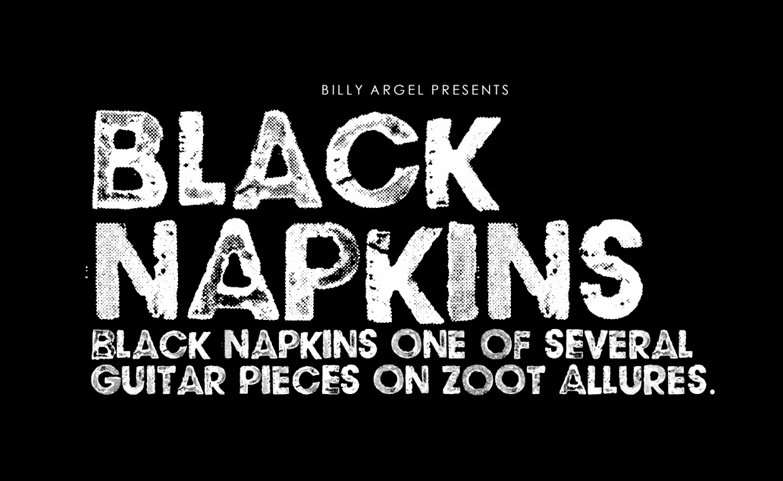
BLACK NAPKINS Font – Download Grátis
A ‘BLACK NAPKINS Font’ é uma elegante escolha para estilos modernos e minimalistas que valorizam a simplicidade. Desenvolvida pelo designer Billy Argel, esta fonte sans-serif traz um toque de elegância sem perder o caráter funcional. Ideal para aplicações digitais em sites, designs gráficos ou qualquer projeto onde uma fonte limpa é essencial. Com seus traços finos e leves, a ‘BLACK NAPKINS Font’ oferece um contraste interessante com texturas menos estruturadas. Suas linhas retas são perfeitas para criar uma identidade visual única em designs que buscam transmitir seriedade ou modernidade. Para uso comercial, o designer disponibiliza as licenças comerciais e a versão completa do font pack no seu site oficial. Compreender essas informações é fundamental para quem busca incorporar esta elegante fonte em projetos profissionais sem infringir os direitos autorais. Visite Billy Argel para explorar mais opções de recursos gráficos, além da ‘BLACK NAPKINS Font’, que oferece uma variedade de opções e estilos únicos. A ‘BLACK NAPKINS Font’ é uma ótima escolha para designers buscando trazer um ar contemporâneo aos seus projetos, sem sacrificar a qualidade ou simplicidade necessárias.
Designer: Billy Argel